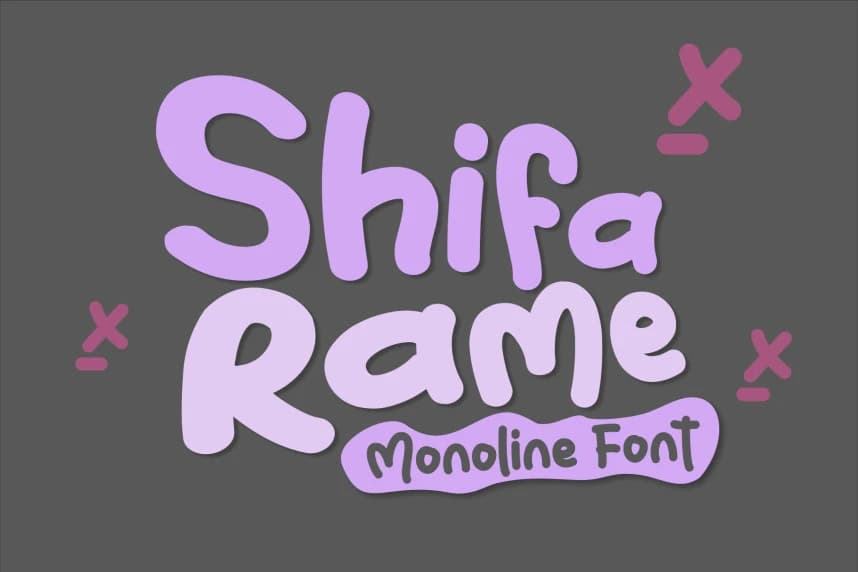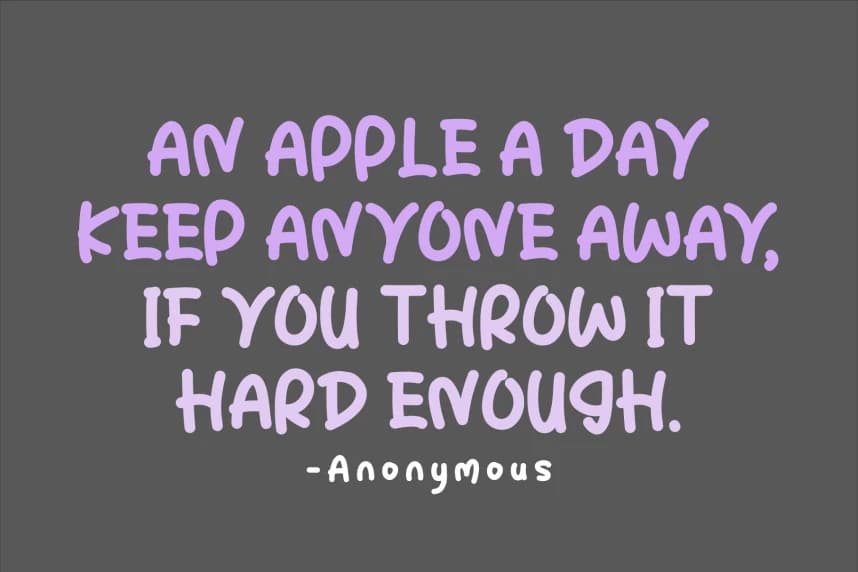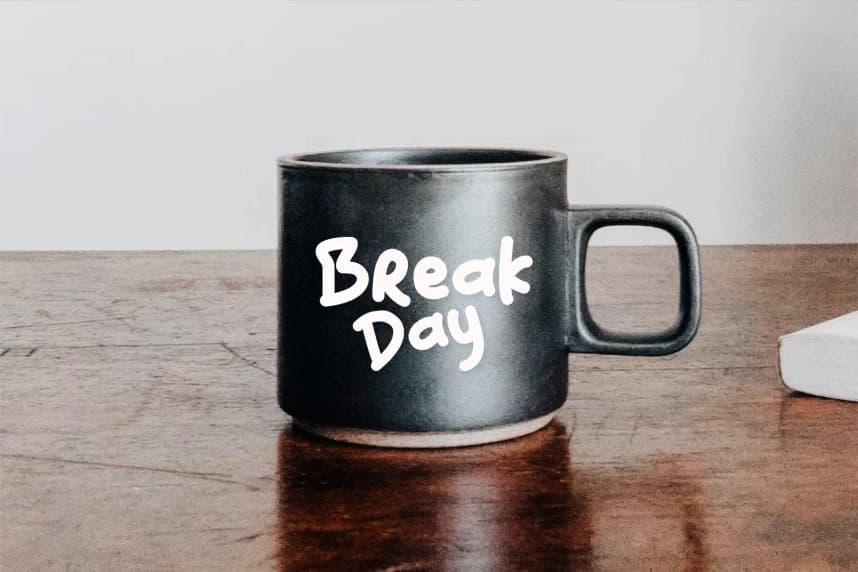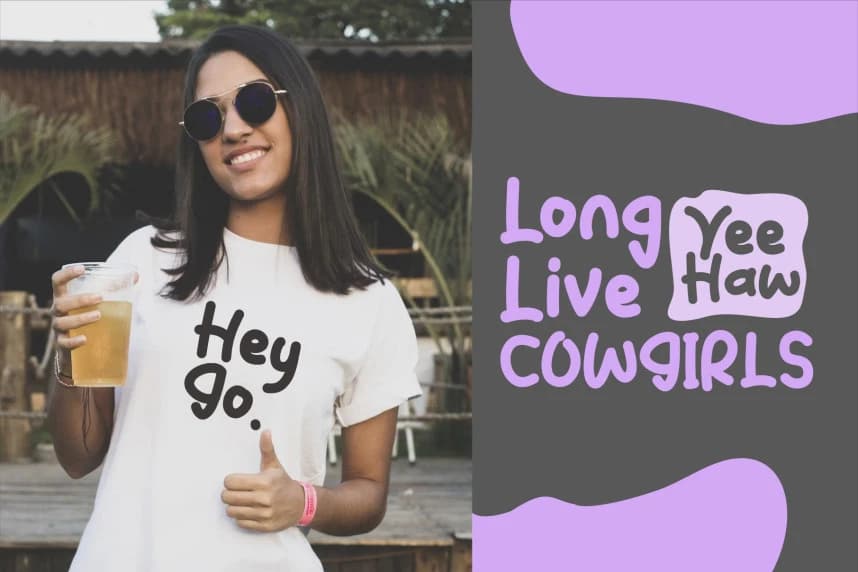
Shifa Rame Font
Shifa Rame Font, sevimli ve gündelik bir gösterim yazı tipidir ve inanılmaz derecede samimi bir hava verir. Instagram için fontlar mı arıyorsunuz yoksa kendin yap projeleri için kaligrafi yazıları mı, bu font herhangi bir yaratıcı fikri gerçek bir sanat eserine dönüştürecek!
Shifa Rame Font, sevimli ve sade bir gösterim yazı tipidir; son derece dostça bir his verir. Instagram için fontlar mı arıyorsunuz yoksa Kendin Yap projeleri için kaligrafi yazıları mı arıyorsunuz? Bu font, herhangi bir yaratıcı fikri gerçek bir sanat eserine dönüştürecek!